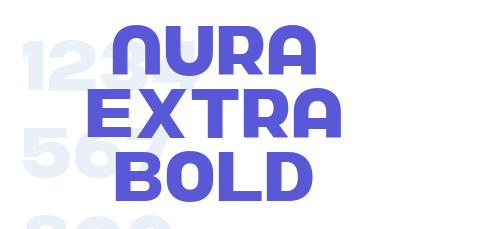
Nura Extra Bold Font Free
Phân loại: Cá tính
Độ dày: Extra Bold
Nura Extra Bold Font là một kiểu chữ đậm và mạnh mẽ, thuộc bộ font chữ không chân. Nura Extra Bold Font được thiết kế thu hút sự chú ý ngay từ cái nhìn đầu tiên. Với các đường nét dày và chắc chắn, Nura Extra Bold Font mang lại cảm giác vững chãi và uy lực, lý tưởng cho các tiêu đề, poster và các thiết kế đòi hỏi sự nổi bật. Kiểu chữ này, không chỉ đảm bảo tính dễ đọc mà còn tạo ra ấn tượng mạnh mẽ, phù hợp cho các thương hiệu muốn thể hiện cá tính và sự tự tin. Đây chính là lựa chọn hoàn hảo cho những dự án cần tạo điểm nhấn rõ ràng và mạnh mẽ trong thiết kế.